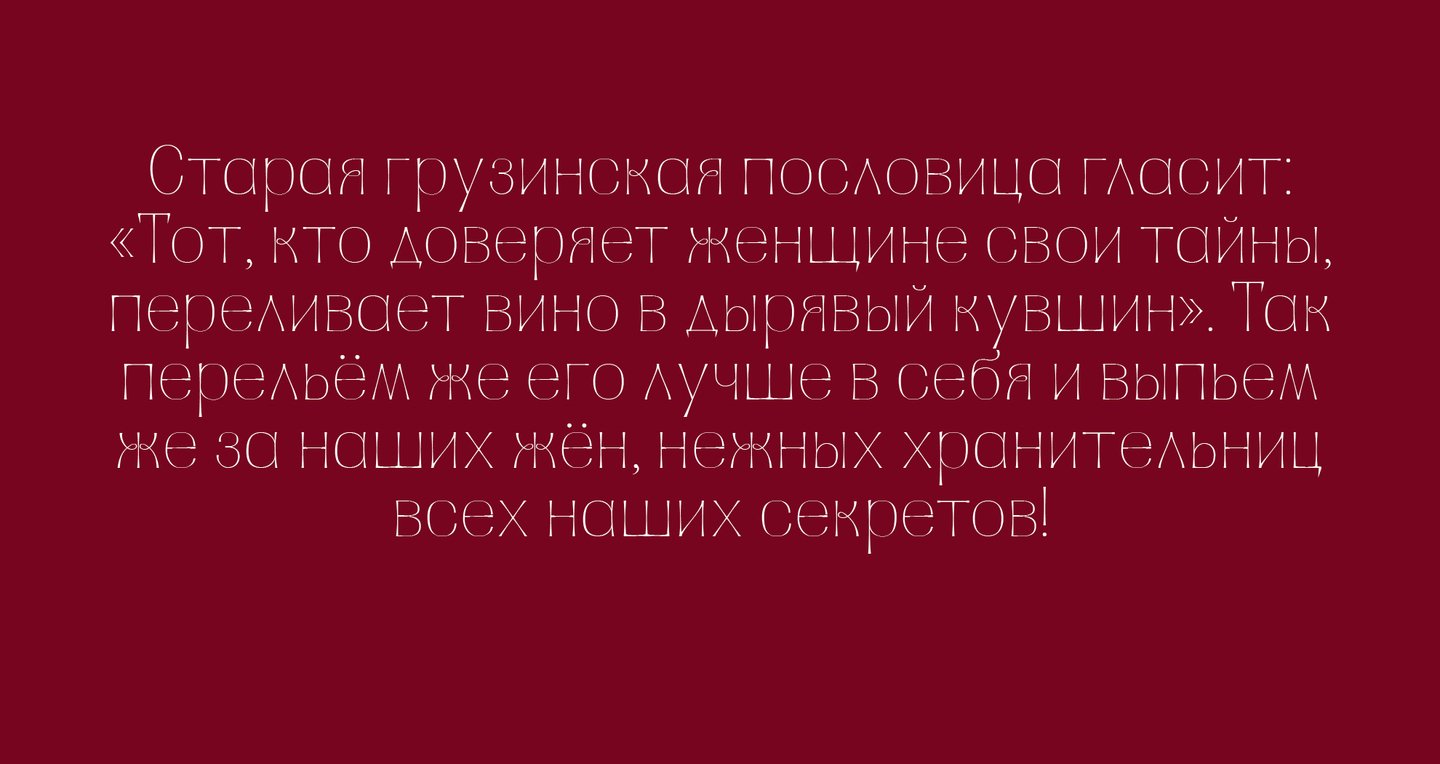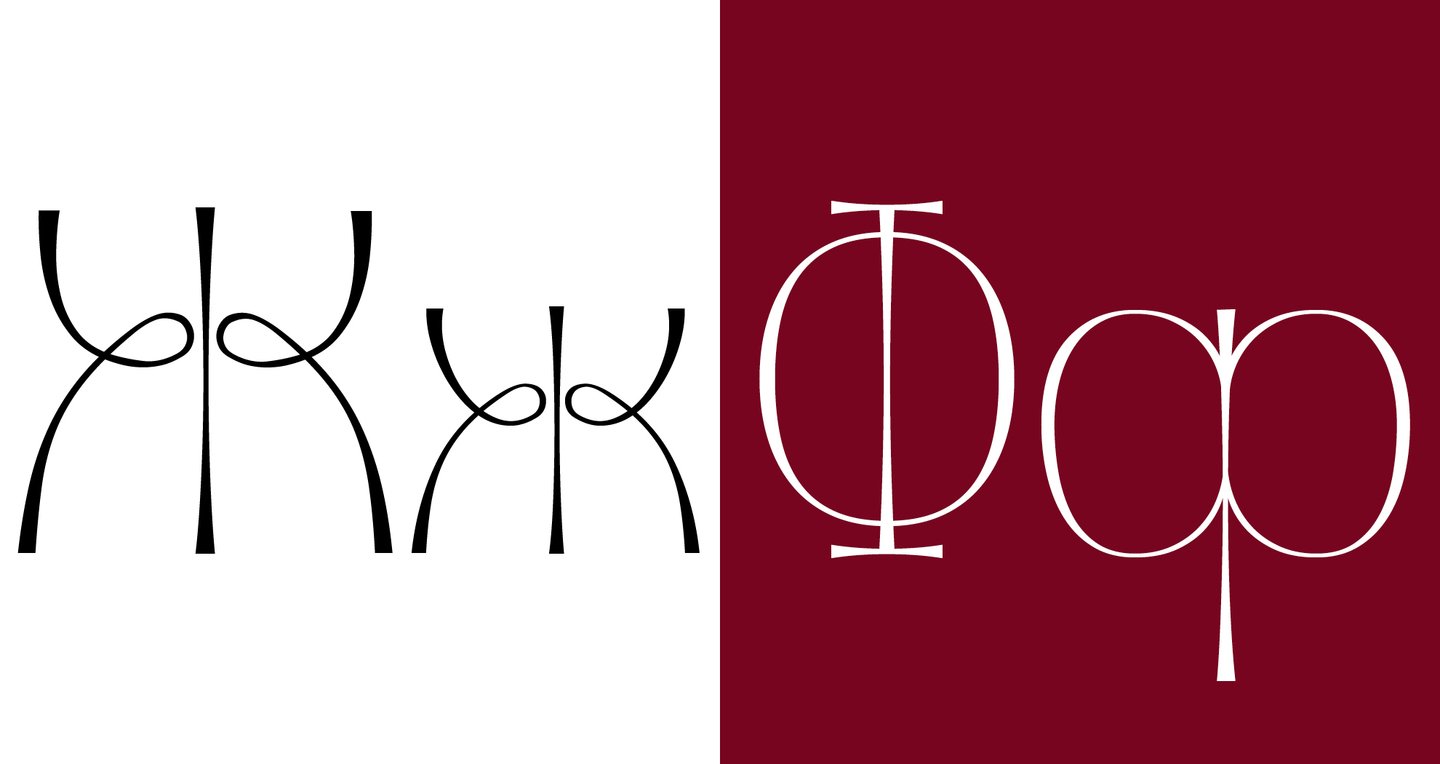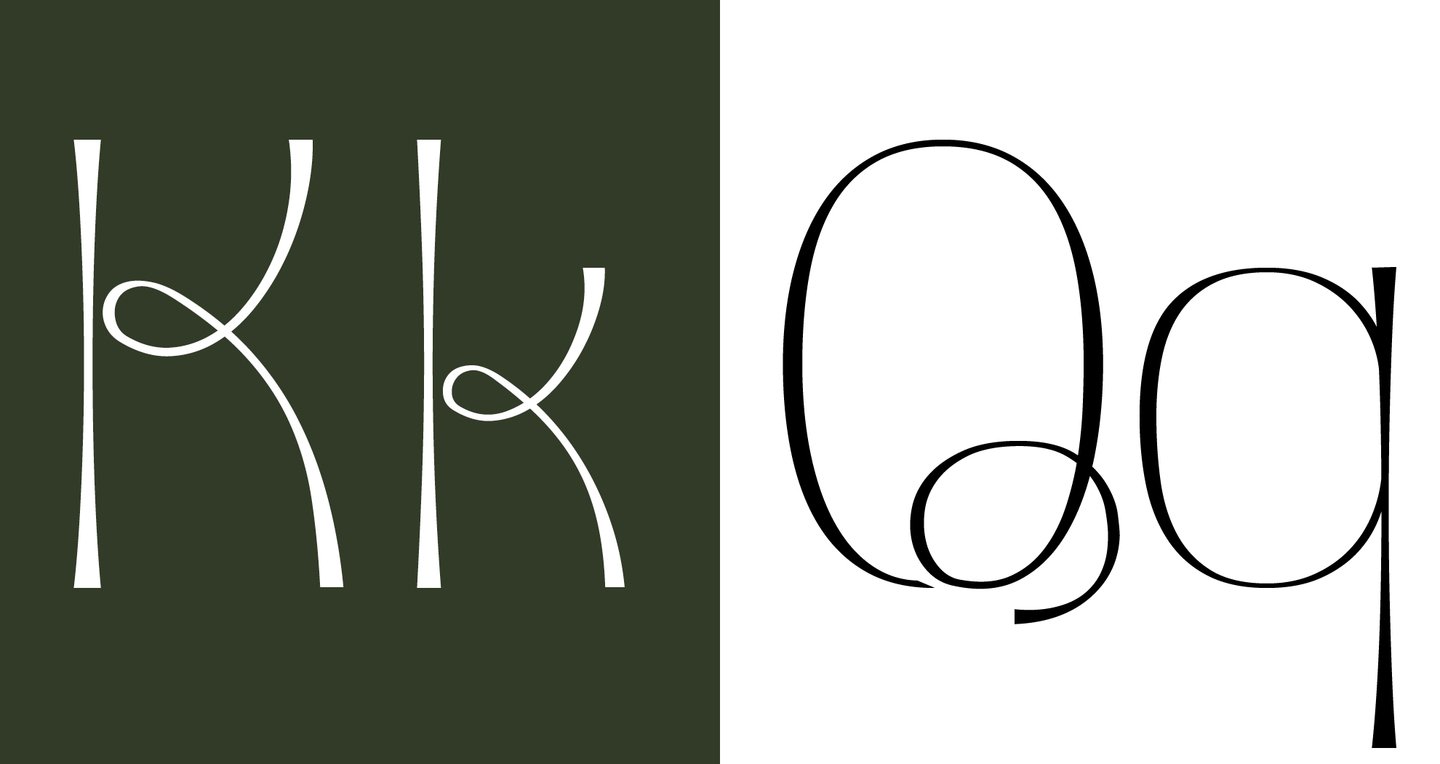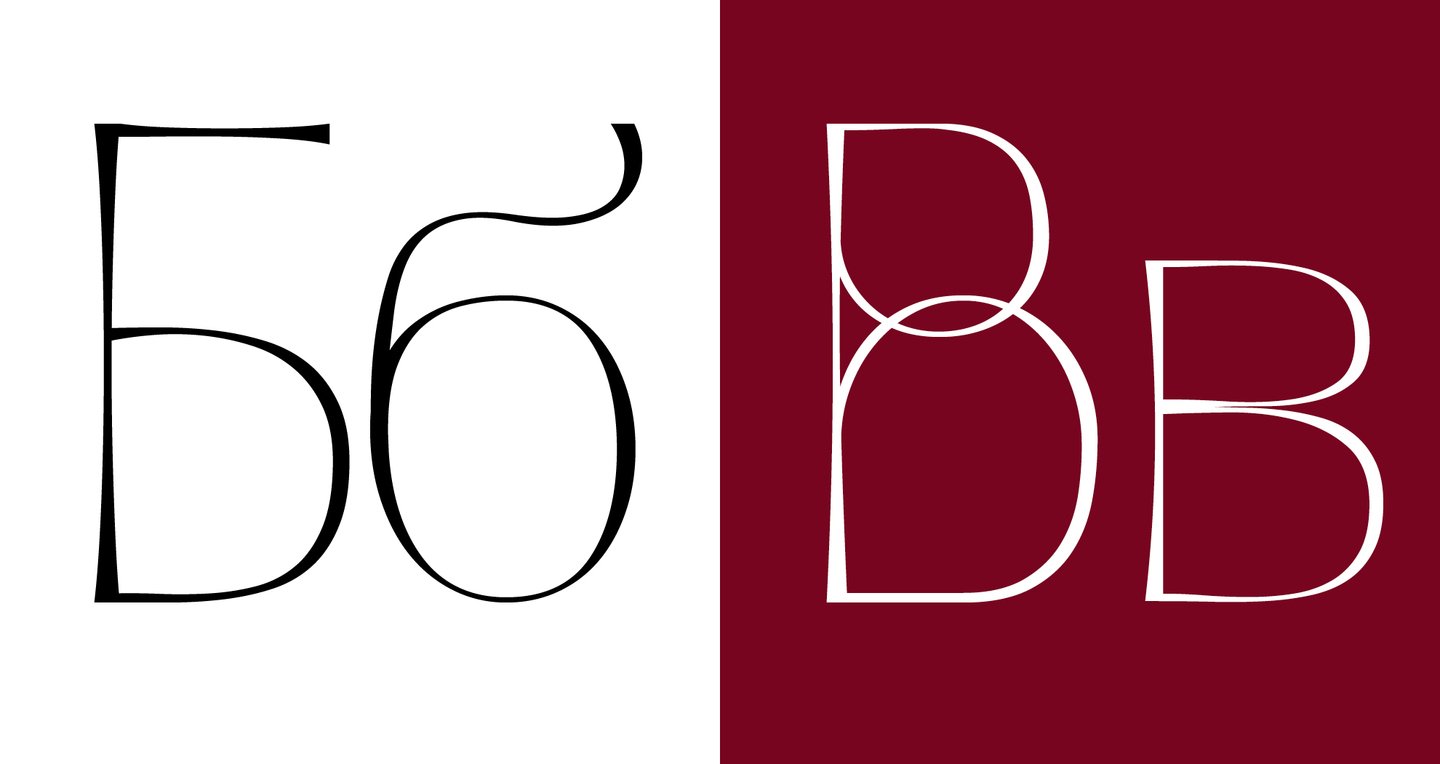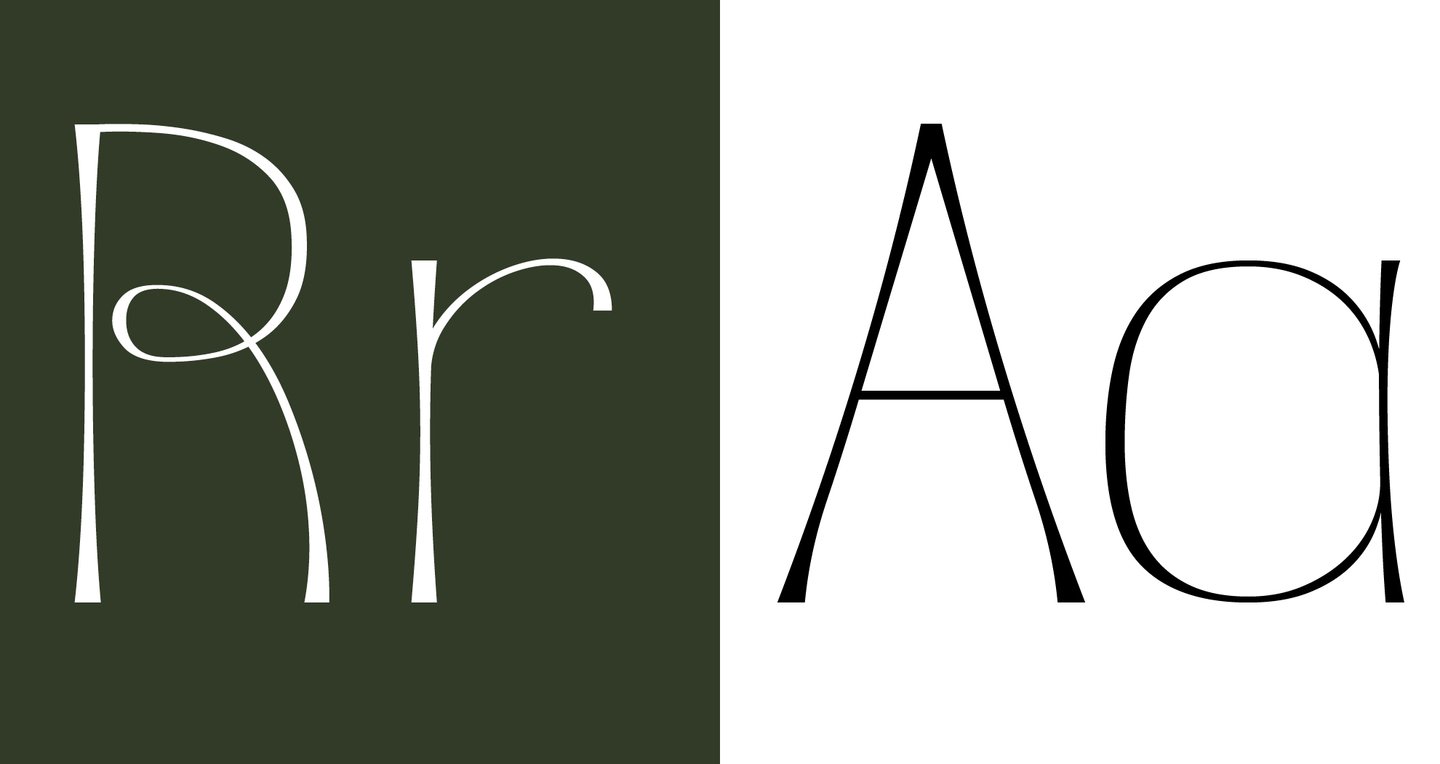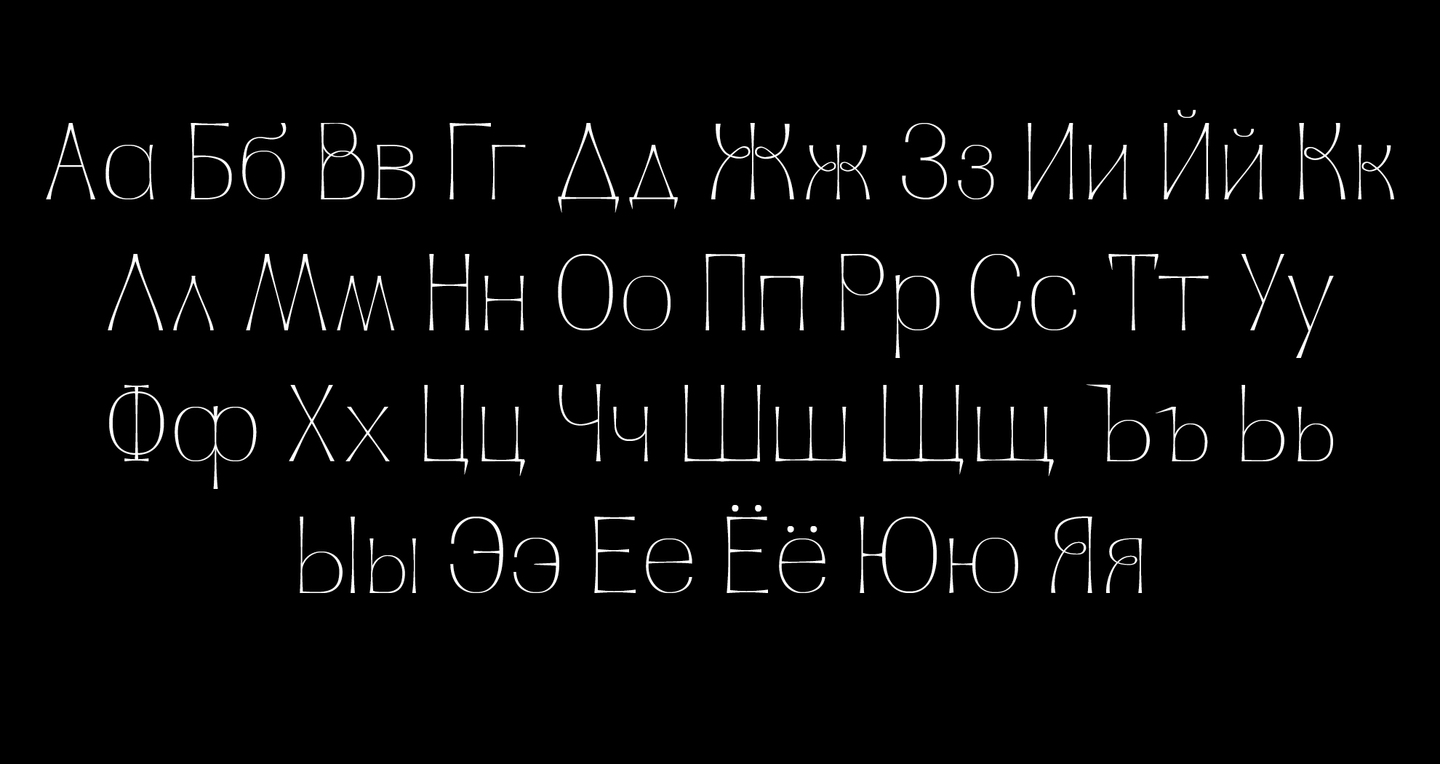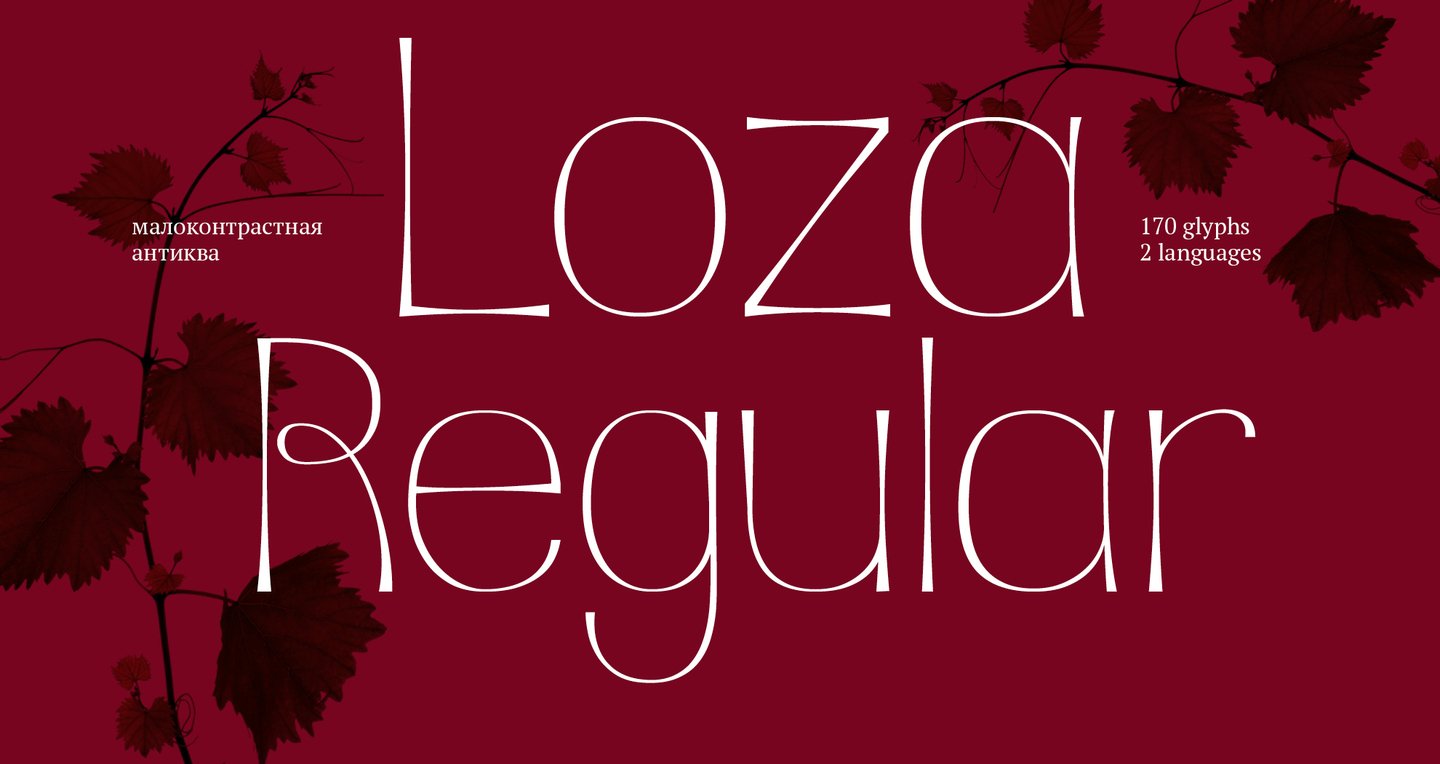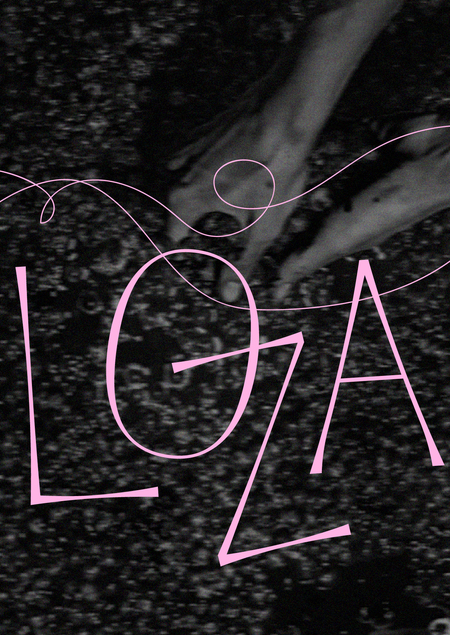
Loza — малоконтрастная антиква, вдохновленная формой виноградной веточки. Шрифт идеально подходит для заголовков винных карт, книг по искусству и поэзии, и в целом проектов с природной, дружелюбной эстетикой